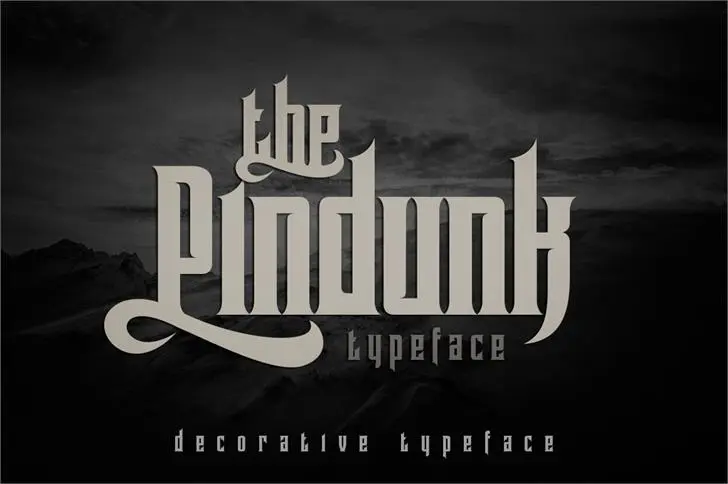
Pindunk Font – Download Grátis
A Pindunk é uma tipografia inspirada no estilo gótico, perfeita para quem busca algo elegante e minimalista em suas criações digitais. O design da Tamavocks oferece um conjunto completo de letras maiúsculas e minúsculas, suporte multilíngue e monetário, números, sinais de pontuação e alternativas, ligaturas e até mesmo alguns caracteres adicionais que adicionam uma dimensão única à sua tipografia. Este estilo gothic é perfeito para o design gráfico moderno, combinando elegância com simplicidade. Experimente a Pindunk em seu próximo projeto e veja por si só como ela pode transformar seus designs em algo excepcional.